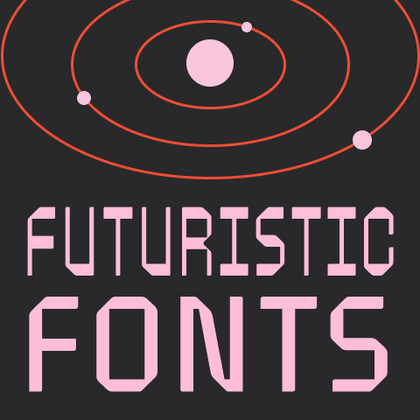
Футуристичные шрифты
Это смелые гарнитуры, воплощающие дух технологий и прогресса. Дизайн футуристичных шрифтов сочетает геометричную четкость, динамичные формы и нестандартные пропорции, создавая эффект «из будущего». В коллекции TypeType такие шрифты идеальны для проектов, где важны современность и запоминающийся визуальный код — от цифровых интерфейсов до космической типографики. Каждая буква здесь становится символом инноваций.
TT Nooks Serif — акцидентная новостильная антиква с лёгким налётом эгоцентричности. У неё острый и твёрдый, при этом элегантный и статный характер.
TT Runs — это выразительный шрифт, который идеально впишется в проекты со спортивной тематикой. При этом гарнитура отлично подойдет и для других современных проектов: после обновления сфера ее применения значительно расширилась.
TT Jenevers стилистически относится к голландским антиквам нового стиля. В гарнитуре присутствуют характерные детали, свойственные голландским антиквам — это ассиметричная форма засечек или нерегулярный наклон овалов.
TT Ricordi Greto — неконтрастный флорентийский гротеск с динамичными пропорциями. Это единственный гротеск среди антикв в коллекции TT Ricordi, при этом в нем сохранились едва заметные засечки, отсылающие к прототипу.
TT Ramillas — стильная и современная антиква. Включает уникальные декоративные начертания и буквицы с цветочным орнаментом.
TT Paplane — акцидентный сквадраченный гротеск. Так, характерные черты этого гротеска — сквадраченные формы, 45-градусные срезы и обтекаемые внешние контуры.
TT Cometus — современная брусковая антиква. Название гарнитуры отсылает к образу кометы — мощного увесистого тела с красивым хвостом, грациозно рассекающего космические просторы с огромной скоростью.
TT Octosquares — октагональный гротеск с футуристическим характером. Этот шрифт отличается геометричностью и своеобразной «мозаичностью»: он как бы собран из отдельных фрагментов, что проявляется и в мельчайших деталях.
TT Carvist — современный экспериментальный гротеск со сверхузкими пропорциями. Название гарнитуры отсылает к резьбе по камню: характерные черты этого шрифта — геометричность и брутальность.
TT Lakes Neue в версии 2.0 — продолжение геометрического гротеска, вдохновлённого финским функционализмом. Новая версия предоставляет больше возможностей, ведь мы не только увеличили кассовый состав и улучшили шрифт технически, но и доработали его визуальный характер.
TT Rounds Neue — гротеск со скругленными формами. В тонких начертаниях шрифт выглядит довольно минималистично и нейтрально: скругленные окончания штрихов становятся практически незаметными, на первый план выходят плавные линии.
Забудьте всё, что вы знали о TT Smalls, ведь мы перевыпустили шрифт! Оформляйте выразительные заголовки, применяйте в оформлении упаковок или выделяйте текст на сайте.
TT Ricordi Marmo продолжает серию экспериментальных гарнитур, созданных в рамках проекта TT Ricordi. TT Ricordi Marmo создавался как плакатный шрифт, поэтому строчной набор в нем заменяет капитель.
TT Norms Std Condensed является логическим развитием нашего бестселлера TT Norms Pro. Несмотря на то, что шрифт обладает более узкими пропорциями относительно исходной гарнитуры, он унаследовал классические пропорции знаков, внимание к деталям и дотошную проработку каждого знака в шрифте.
TT Tsars является коллекцией акцидентных титульных антиквенных шрифтов, стилизованных под начало, середину и конец XVIII века. В основу проекта легли титульные шрифты, то есть те шрифты, которыми оформлялись, в частности, книжные титулы.
При проектировании TT Mussels мы уделили большое внимание возможности верстать большие массивы текста и можем ответственно заявить, что TT Mussels является редким видом технологических текстовых шрифтов.
Первоначально идея шрифтового семейства TT Milks заключалась в том, чтобы создать коллекцию шрифтов для использования в упаковке и брендинге молочной продукции.
TT Lovelies Script является очень живым и игривым шрифтом с небольшими нюансами непредсказуемости. В нем даже прописные буквы соединяются со строчными во всех случаях без разрывов. Каждая строчная буква имеет характерные росчерки, начинающие и заканчивающие слово.
TT Corals — это современный гуманистический гротеск, который имеет очень много характерных исторических черт начала 20-го века. Шрифт хорошо подойдет для темы классической литературы или музыки, а также для других самых разнообразных творческих областей человечества.
TT Octas — шрифтовое семейство с узкими пропорциями, построенное по принципу октагональности, в данной гарнитуре все окружности представляют из себя восьмигранники. Благодаря небольшим засечкам Октас приобретает насыщенный и старинный характер.
Любите ли вы раннюю советскую визуальную культуру как любим её мы? Несмотря на свое советское прошлое, TT Bricks выглядит очень свежим и визуально мощным шрифтовым семейством, которое отлично вписывается в современное медиапространство.